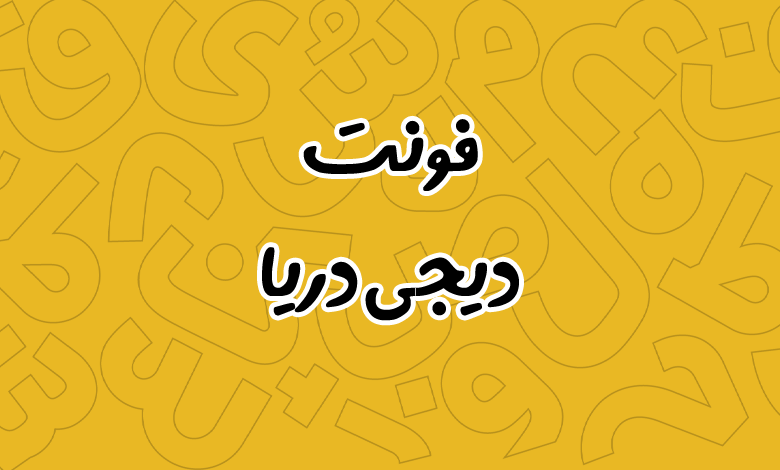
فونت دیجی دریا (Digi Darya)
فونت دیجی دریا یا فونت دریا (به انگلیسی: Digi Darya) یکی از بهترین قلمهای آزاد در سبک دست نویسی با قلموی انگشتی (سبک دیستورت) است که میتوانید از این قلم زیبا برای متون کوتاه و نمایشی استفاده کنید. در ادامه با دانلود فونت دیجی دریا با شما همراه هستیم.
فونت دیجی دریا توسط مهدی برقگیر در سبک قلمو انگشتی طراحی شده است که از هر سه زبان فارسی، عربی و انگلیسی پشتیبانی کاملی دارد. این فونت فارسی رایگان از یک وزن بولد پشتیبانی میکند که برای استفاده در عناوین و متون کوتاه کاربردی است.
فونت دریا فارسی محدود به این زبان نیست و به منظور استفاده در پروژههای چند زبانه از زبلان عربی و انگلیسی نیز پشتیبانی میکند. در این فونت دستنویس فارسی کلیه گلیفهای استفاده شده برای هر زبان به شکل استاندارد طراحی شده است.
حروف در این فونت با ضخامت بولد طراحی شدهاند و از سبک نقطهگذاری پیوسته برای آن استفاده شده است. ضخامت حروف یکسان نبوده و در برخی موارد مثل منحنیها نسبت به خطوط افقی و عمودی، ضخامت بیشتری اعمال شده است. چشمیها در این فونت دارای ضخامت کمتری هستند هرچند که برای حروفی مثل «هـ، ـهـ، ه» از ضخامت بیشتری در یکی از چشمیها استفاده شده است.
فونت digi darya انگلیسی نیز دارای گلیفهای استاندارد خود است که به منظور نمایشی کردن و ظاهری هماهنگ با نسخه فارسی، برخی حروف لاتین در این فونت دارای سبکی هایلایت شده هستند. مانند حروف «m, n» ک در تصویر پیش نمایش نیز نمونه آن را میبینید.
این فونت رایگان دست نویس تنوع بالایی برای حروف و ترکیبات جایگزین دارد. بهطوری که میتوانید با استفاده از کلیدهای ترکیبی SHIFT + M یا قرار دادن ء در انتهای برخی حروف مانند «ی، ـی، س، ش» امکان تایپ متفاوت حروف و ترکیبات را داشته باشید. از این فونت با توجه به ترکیباتی که دارد میتوانید در محیطهای زیر استفاده کنید:
- استوری و پست شبکههای اجتماعی
- کاور ویدئوهای یوتوب
- شعارهای تبلیغاتی
- جملات انگیزشی و عکس نوشته
- عناوین و جلد کتاب بهویژه در حوزه کودک و نوجوان
در این فونت همچنین از قابلیت اعرابگذاری هوشمند برای زبان عربی استفاده شده که برای کارهای عکسنوشته یا مذهبی میتواند گزینه خوبی باشد. این ویژگی به افزایش زیبایی طرح شما کمک میکند. این قلم یکی از پر استفادهترین پک فونت فارسی برای کپ کات و اینشات است.